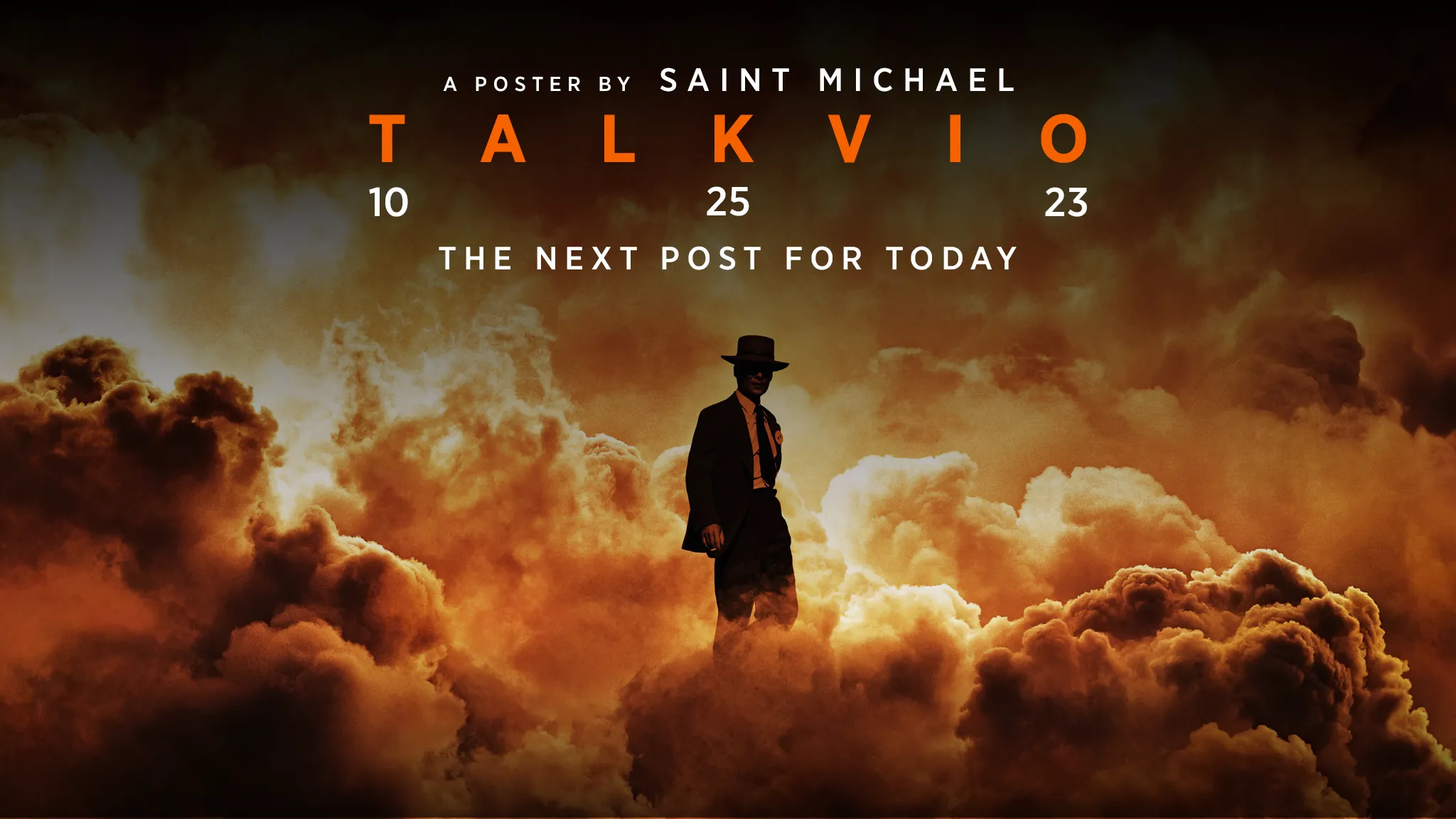
Для фильма «Оппенгеймер» была создана некая модификация шрифта «Gotham», которая слегка меняет написание буквы «о».
Оригинальный «Gotham» это современный и элегантный шрифт, который много где применяется. Даже использовав не модифицированную версию, широко раздвинув буквы, можно добиться эффекта «Оппенгеймера».
P.s. Иронично, что Нолан использовал шрифт «Готэм», не правда ли?)